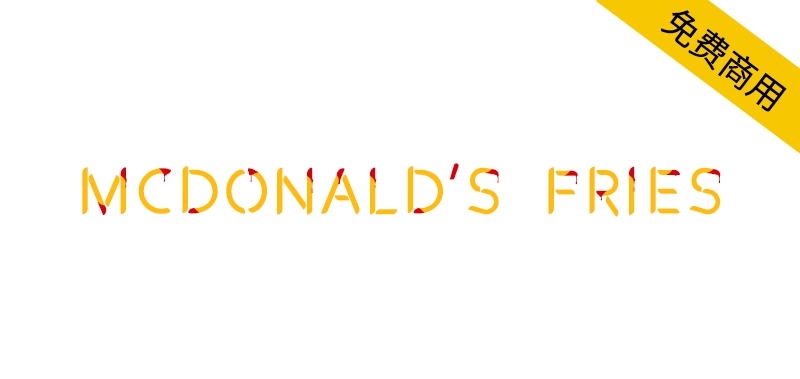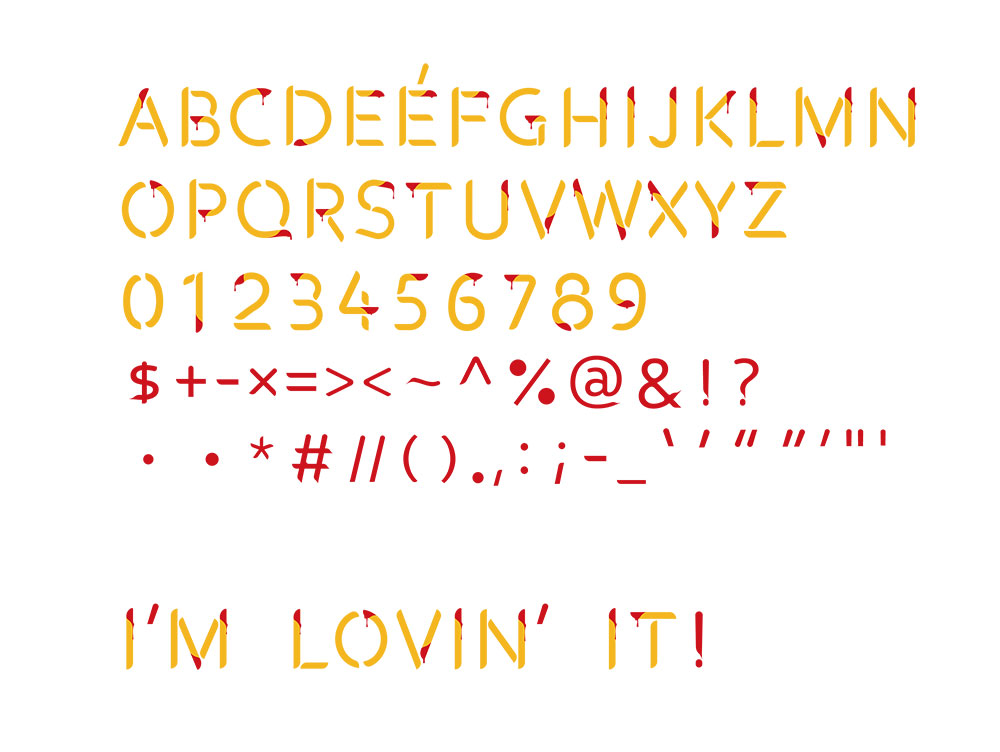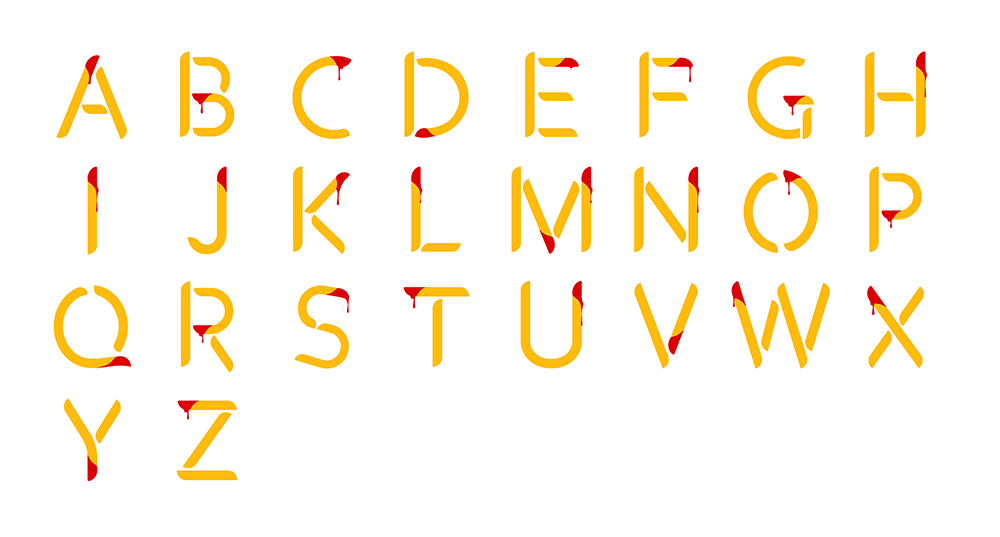
麦当劳薯条体(McDonald’s Fries Font)以麦当劳薯条为设计灵感,巧妙地将薯条和番茄酱融入字体的构建之中,不仅创意十足,更展现出独特的个性。
为每⼀位热爱薯条的麦当劳铁粉献上— 麦当劳薯条体。 薯条vs 番茄酱一起闹一下! 酥脆绵密的薯条、沾上美味番茄酱,拼出无限可能。 麦当劳薯条体,免费开放下载! ※ 字型仅支持部分绘图软体与作业系统,另附PNG档可下载自由拼凑。